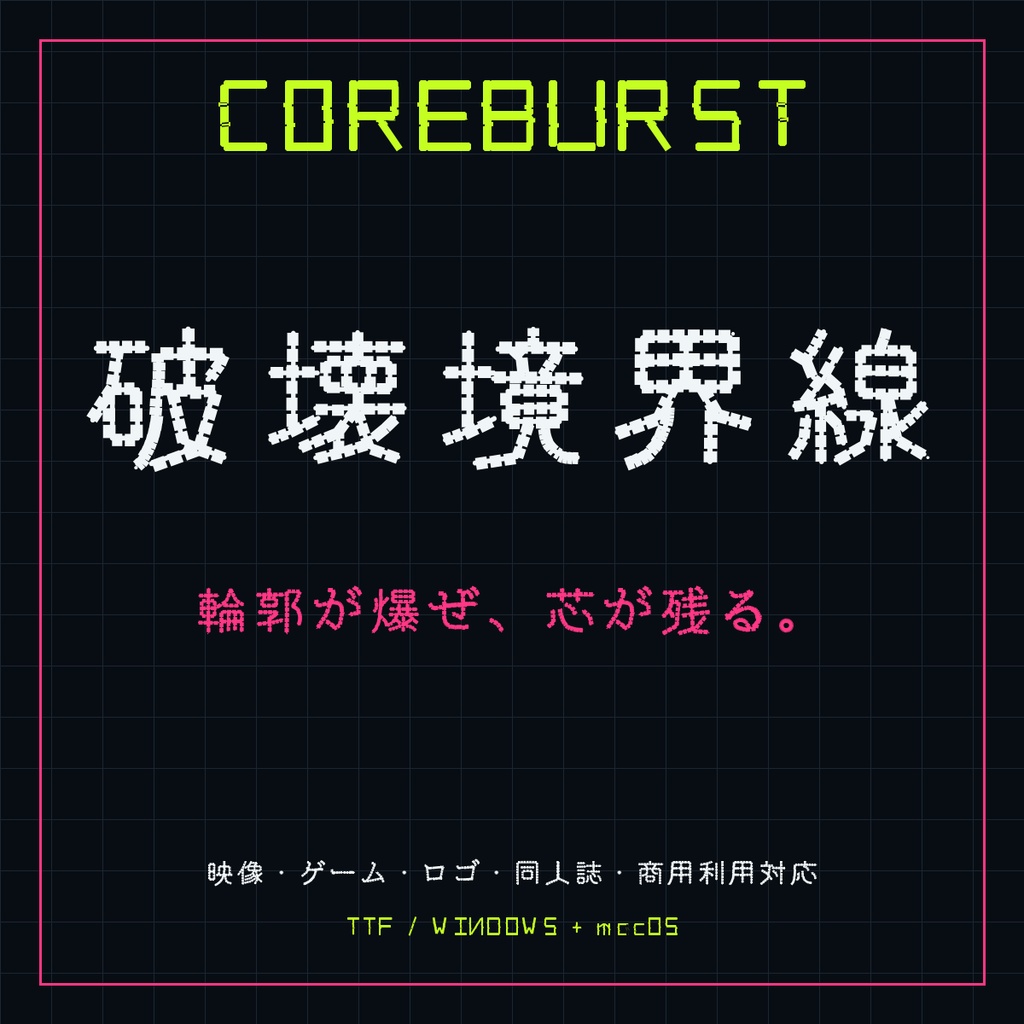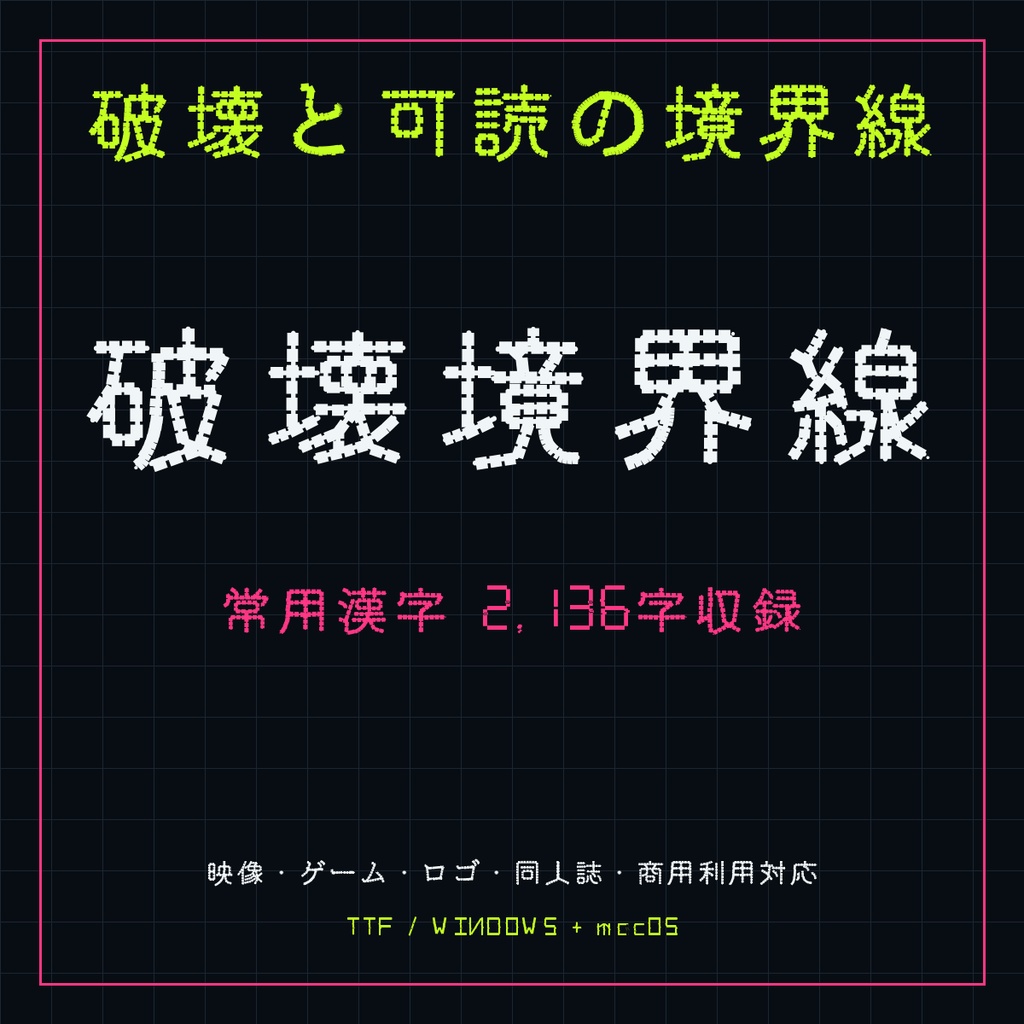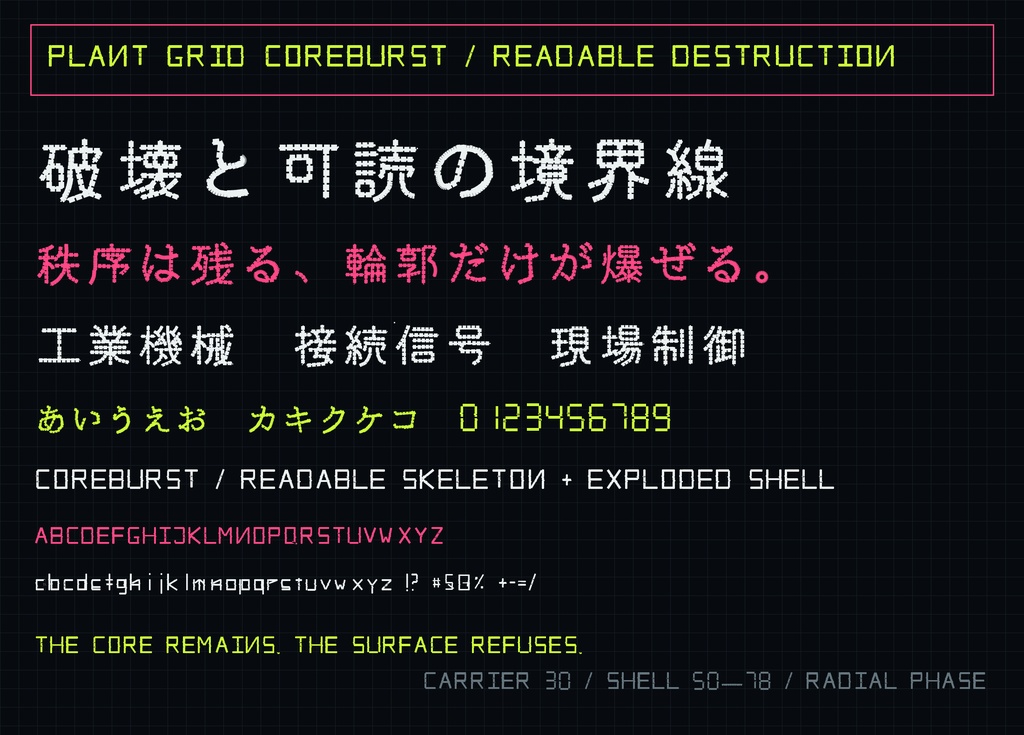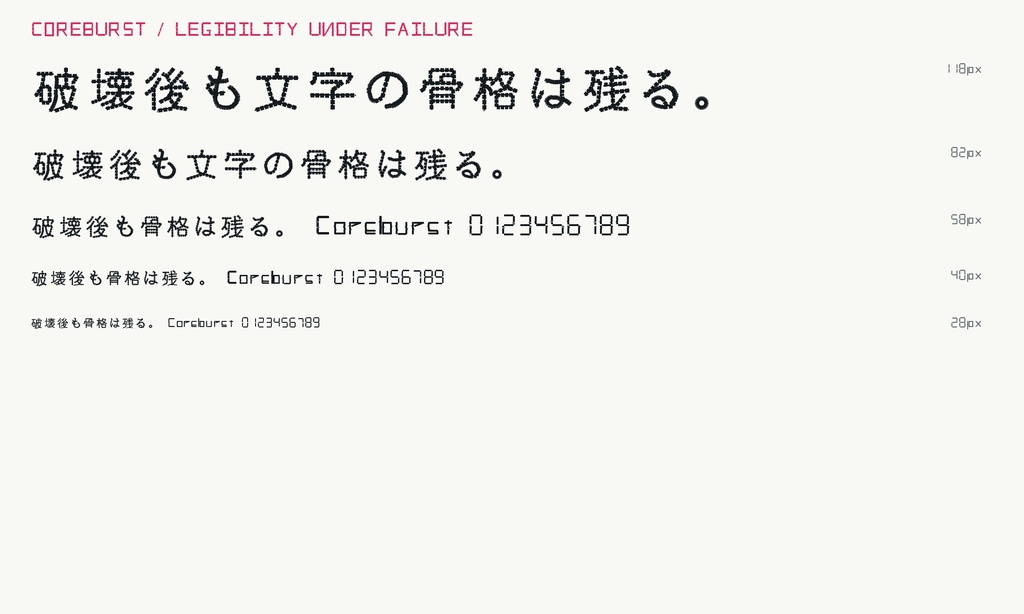
【COREBURST / コアバースト】輪郭が爆ぜる日本語フォント|常用漢字2,136字収録
【COREBURST(コアバースト)】 読み取れる芯線を残しながら、太い輪郭だけが外側へ爆ぜる日本語ディスプレイフォントです。小さく置くと荒れた工業書体として、大きく置くと破片と衝撃のディテールが現れます。 ゲームタイトル、MV・映像、配信画面、同人誌、ロゴ、警告表示、サイバー/終末世界系デザインに。 ■ 価格 980円 ■ 形式 TrueType(TTF) / Windows・macOS ■ 収録 2540文字マッピング 常用漢字:2136字 ひらがな・カタカナ・英数字・基本記号 ■ 利用 個人・商用利用可。ロゴ、動画、ゲーム、印刷、配信、同人・商業作品に使用できます。クレジット不要。フォントデータの再配布・共有・転売は禁止です。詳細はZIP内の利用規約をご確認ください。 ※見出し・タイトル向けの装飾書体です。本文や小サイズでは細部がつぶれる場合があります。